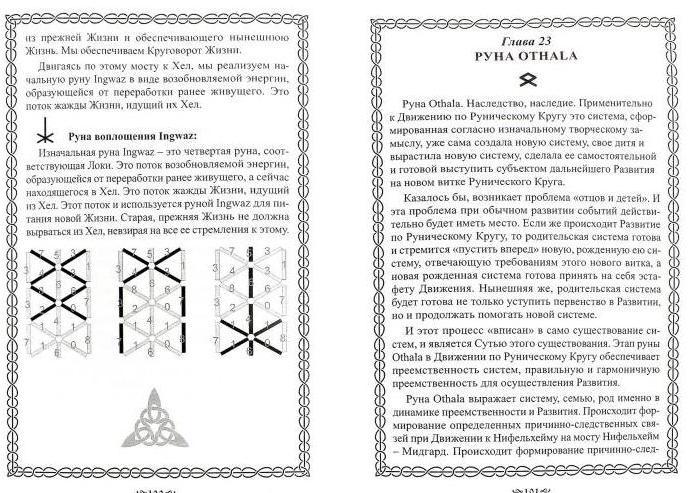
Готовьтесь к волшебству: уникальные шрифты, воплощающие руны
Изучите особенности использования шрифтов, которые смотрятся как древние руны, и создайте волшебный эффект на вашем веб-дизайне или графических работах.
Выберите подходящий шрифт, который имеет рунообразный стиль.
Рассмотрите символику рун и выберите соответствующие символы для использования в вашем дизайне.
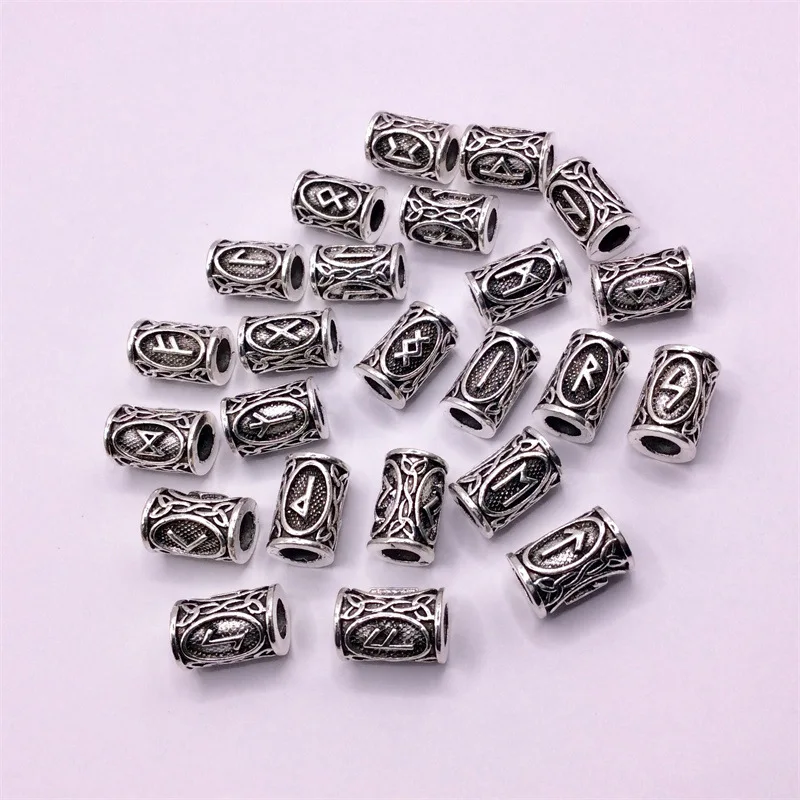
Добавьте дополнительные эффекты, такие как текстуры или световые отблески, чтобы усилить магическую атмосферу.
Экспериментируйте с разными размерами и расположением рун, чтобы найти наилучшую композицию.
Используйте эти шрифты для создания заголовков, логотипов или иных важных элементов дизайна, чтобы они привлекали внимание и вызывали интерес.
Не забывайте проверять читаемость текста, особенно при использовании узорных или экспериментальных шрифтов.
Персонализируйте выбранный шрифт, чтобы он соответствовал вашему уникальному стилю и впечатлению.
Работайте с цветовой палитрой, чтобы добавить глубину и насыщенность вашей композиции.
Создайте свою коллекцию уникальных рун, чтобы использовать их в будущих проектах.
Не бойтесь экспериментировать и быть творческими - рунообразные шрифты отлично подходят для нестандартных дизайнерских решений. Леруа личный кабинет юр лица